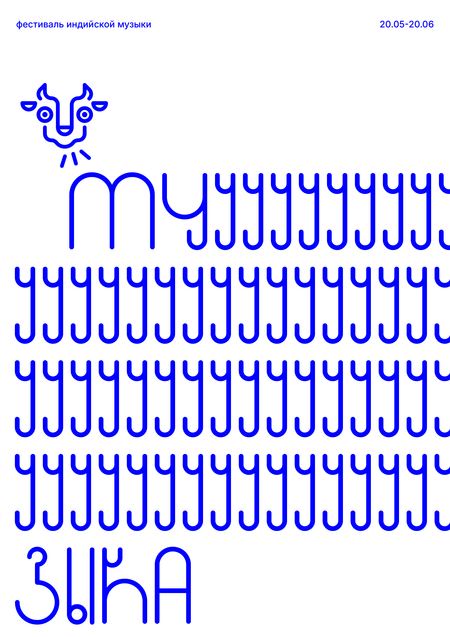
Mooosic font
Дарья Агафонникова
Акцидентная брусковая антиква с квадратными пропорциями и акцентными острыми засечками и чёткой геометрией. Шрифт вдохновлен образом комбайна «Нива СК-4» из мультфильма «Ну, погоди!» Квадратные пропорции формируют плотный, устойчивый ритм, а острые засечки добавляют графической остроты и динамики.